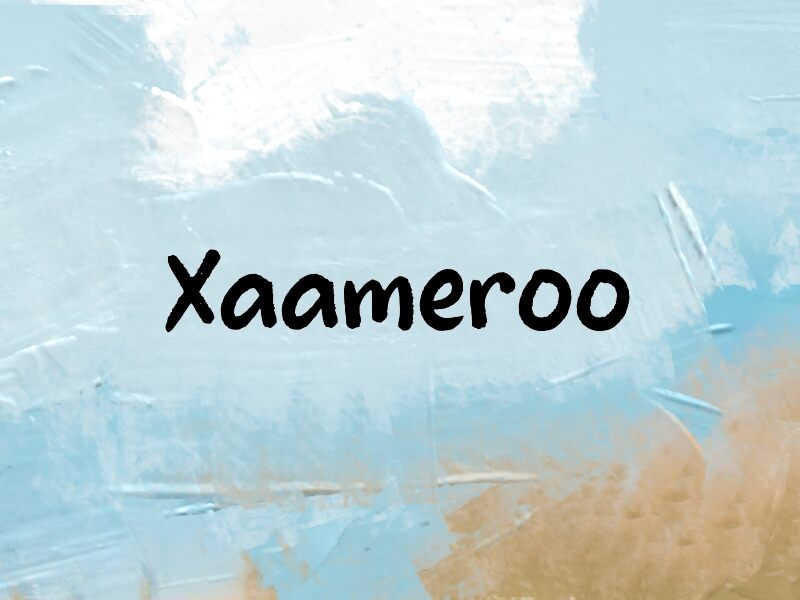
Xaameroo от Wep — это бесплатный шрифт в стиле кисти с грубым, «рукописным» ритмом, который ощущается максимально неформально и живо. Буквы выглядят широкими и насыщенными, с легкой неровностью, плотными штрихами и слегка небрежными краями, что не дает шрифту выглядеть слишком прилизанным или выверенным.
Он отлично подходит для заголовков плакатов, оформления музыкальных релизов, обложек зинов, брендинга кофеен и быстрых постов в соцсетях — везде, где нужен бесплатный шрифт с сырой энергией мазка кисти, но без лишнего официоза. Поскольку формы здесь скорее массивные и свободные, чем изящные, Xaameroo также хорош для коротких заголовков, акцентов на упаковке и простых логотипов, которым не хватает рукописного драйва.
Презентация и наглядный образец шрифта Xaameroo